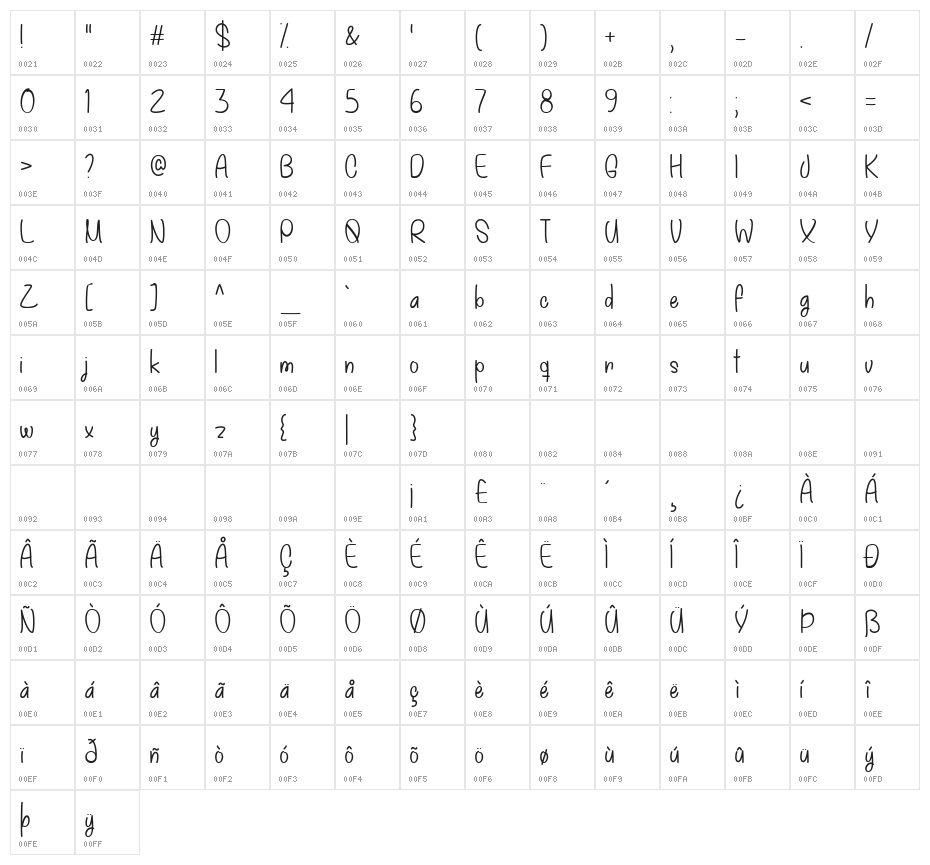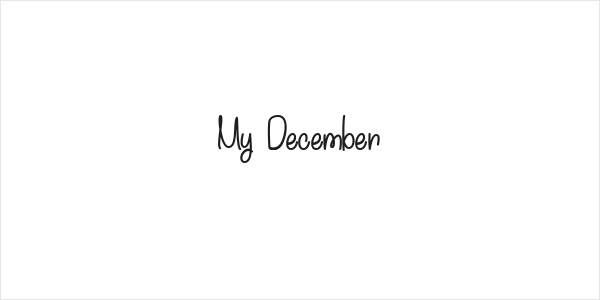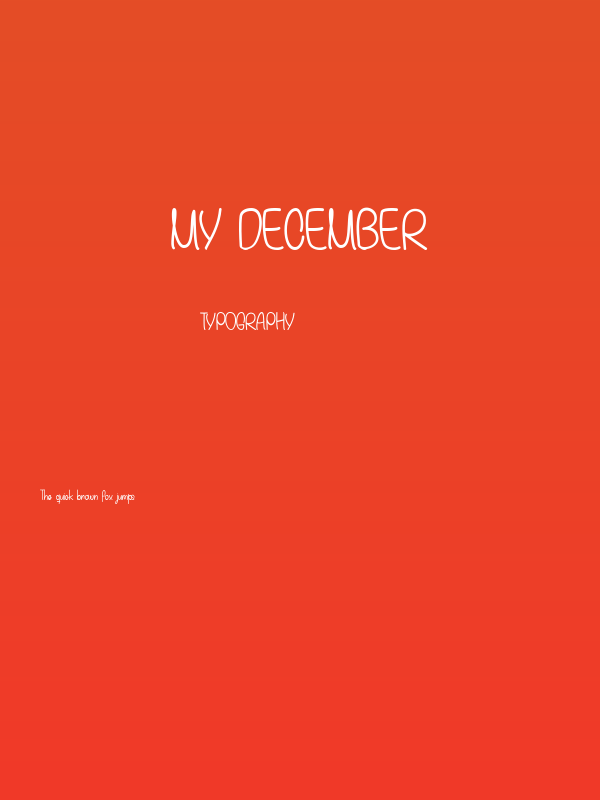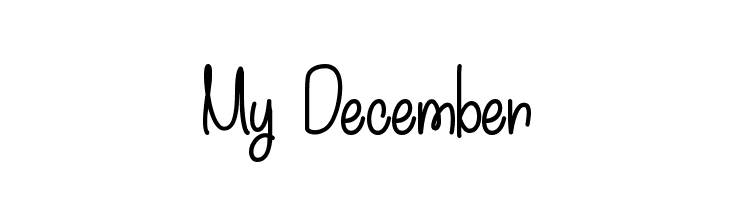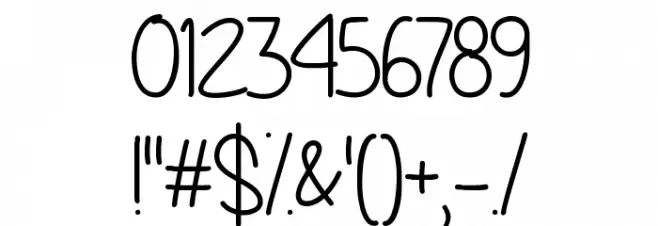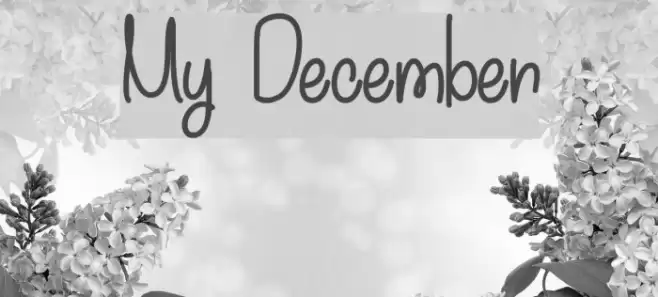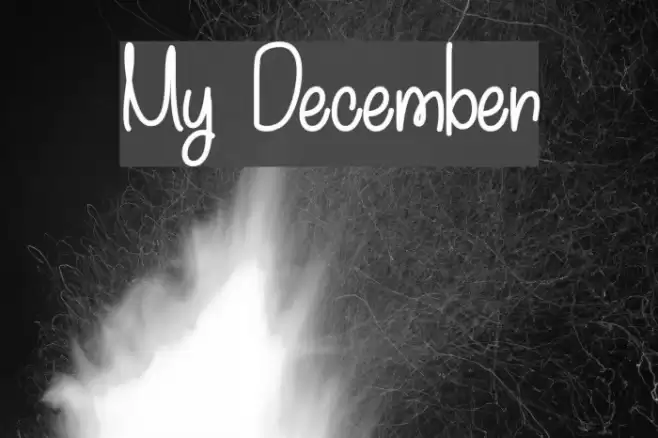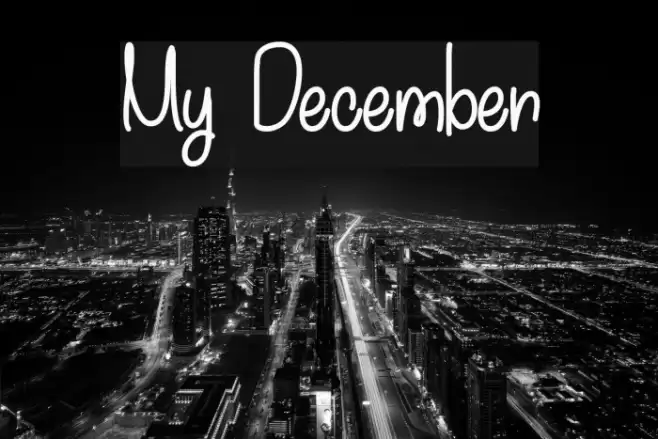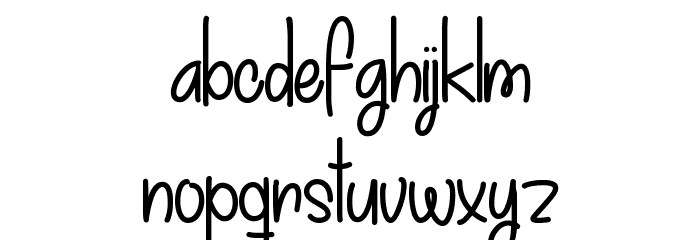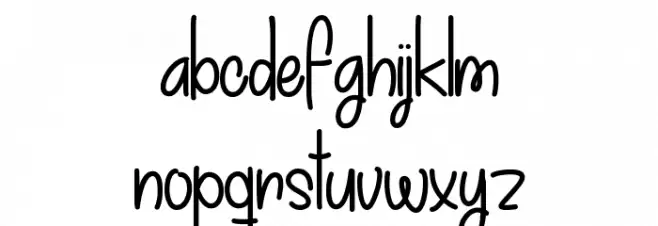
My December Font
| Gesamtstil | Playful |
| Anwendungsfall | Headlines, Logos, Invitations |
| Vorgeschlagene Projekte | Ideal for children's books, greeting cards, playful branding, and casual invitations. |
My December